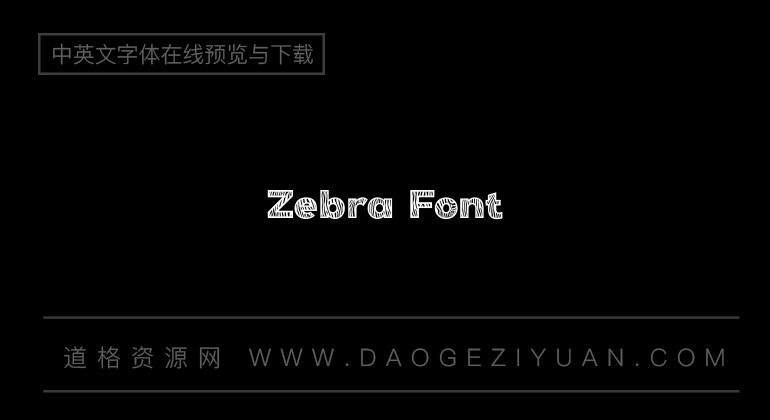
Zebra Font 是一种显示字体,它的特点是每个字符都有黑白条纹图案,类似于斑马的图案,因此得名。这种字体常用于商业和广告设计中,因为它具有强烈的视觉效果和易于辨认的特点,可以使文字更加引人注目和易于记忆。Zebra Font 可以在许多不同的文件格式中使用,包括 TTF、OTF、WOFF 等。此外,它也可以在许多不同的应用程序中使用,例如 Microsoft Word、Adobe Photoshop 等,使得设计师和创意人员可以轻松地将其应用于他们的项目中。内容介绍
Zebra Font是一款非常不错的手写艺术字体,具有很好的视觉感,适合于文化类的宣传设计、商业类品牌的广告和产品包装设计以及个性化文字排版等较多场景。